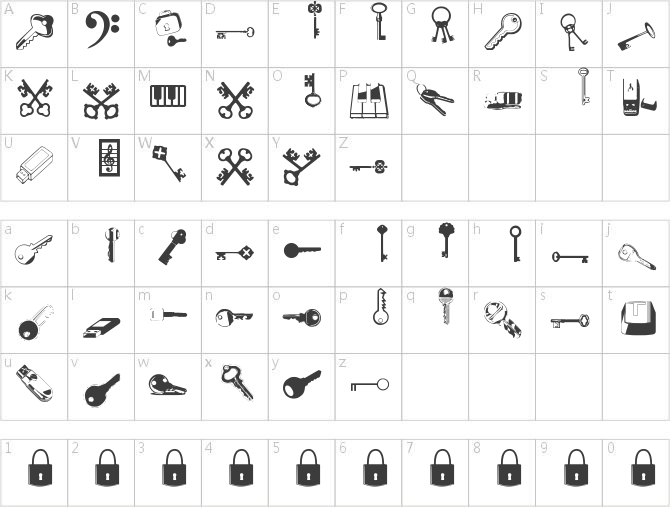
字體名稱: SamysKe
SamysKeysNKeys
SamysKeysNKeys字體字庫(kù)是一款讓人賞心悅目、百看不厭的英文字體,適合各類廣告和產(chǎn)品包裝設(shè)計(jì)應(yīng)用,字體大小0.05MB,格式為ttf字體,上傳用戶是小黑,作者/版權(quán)方為未知